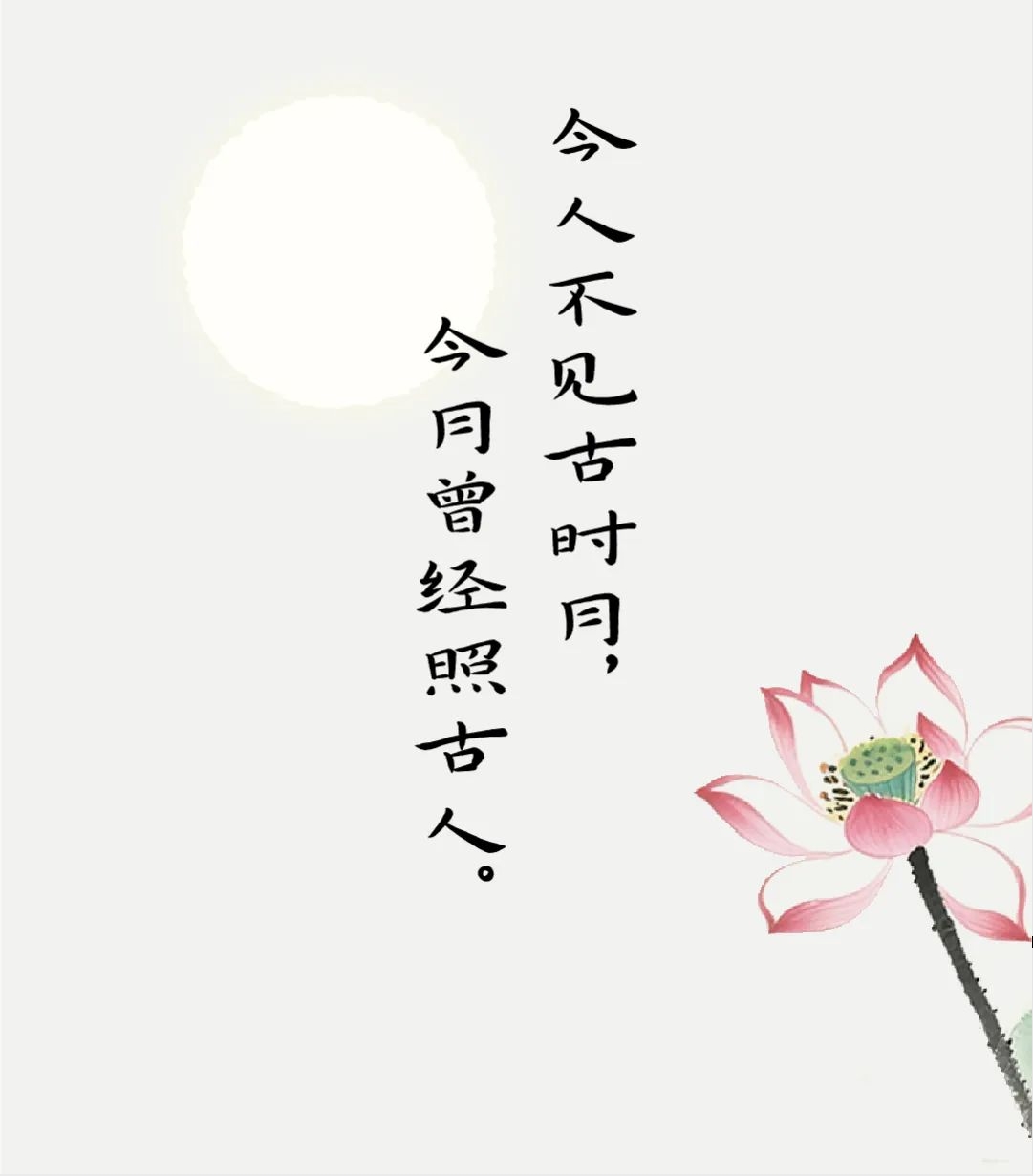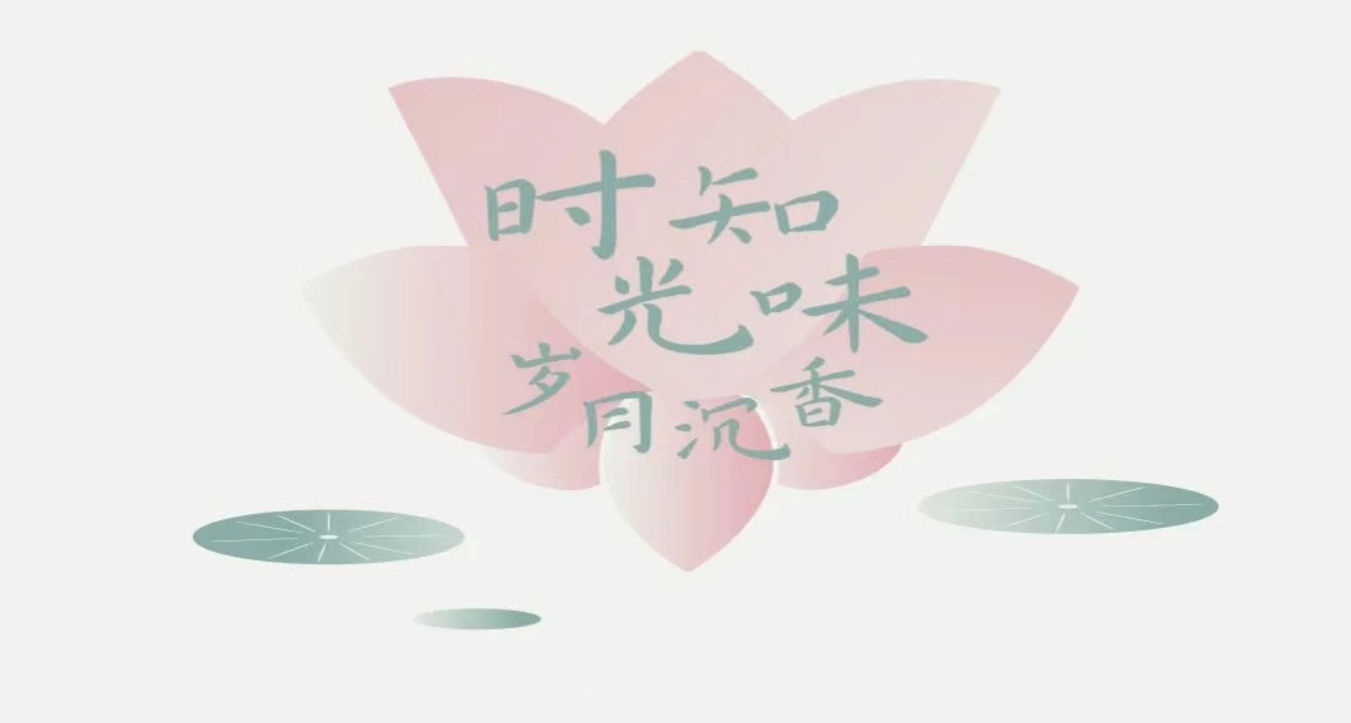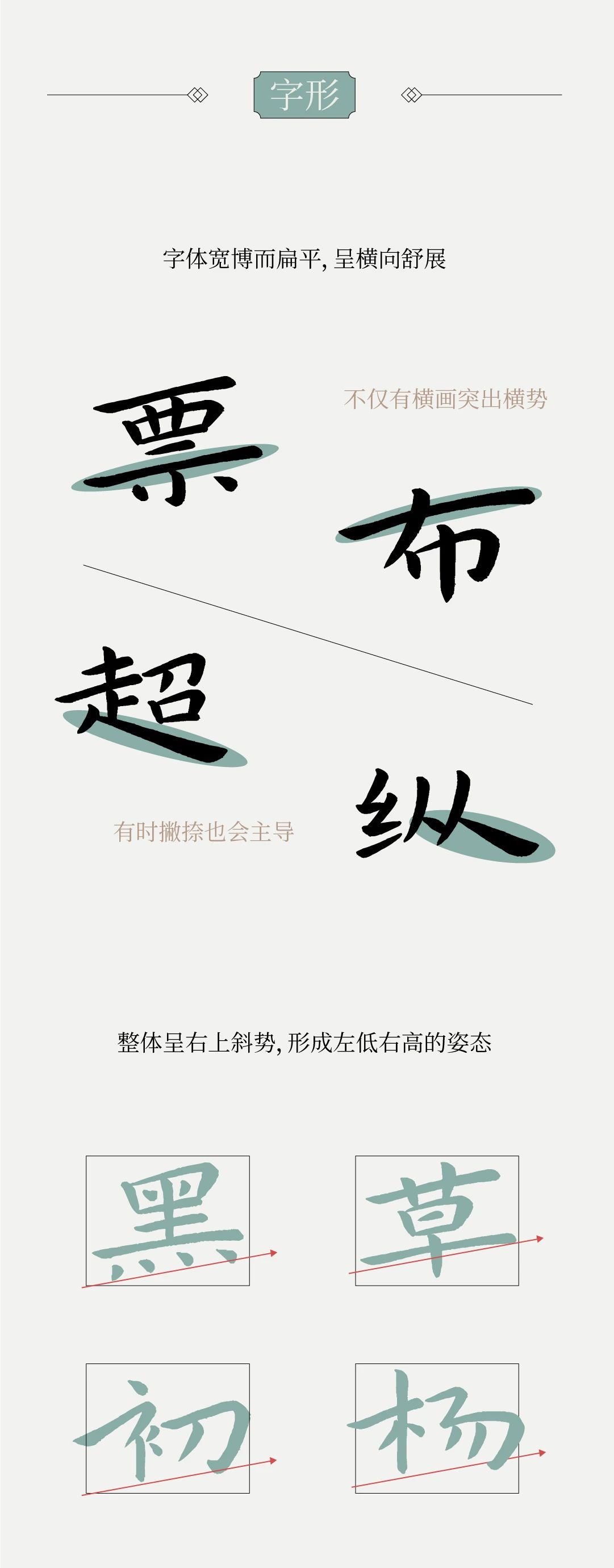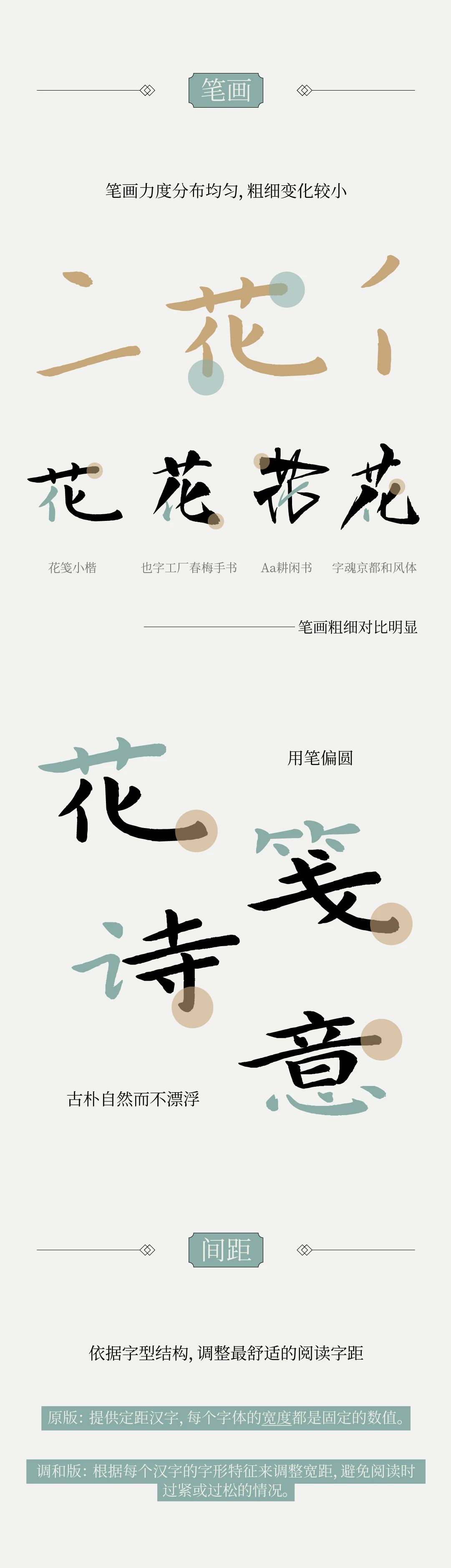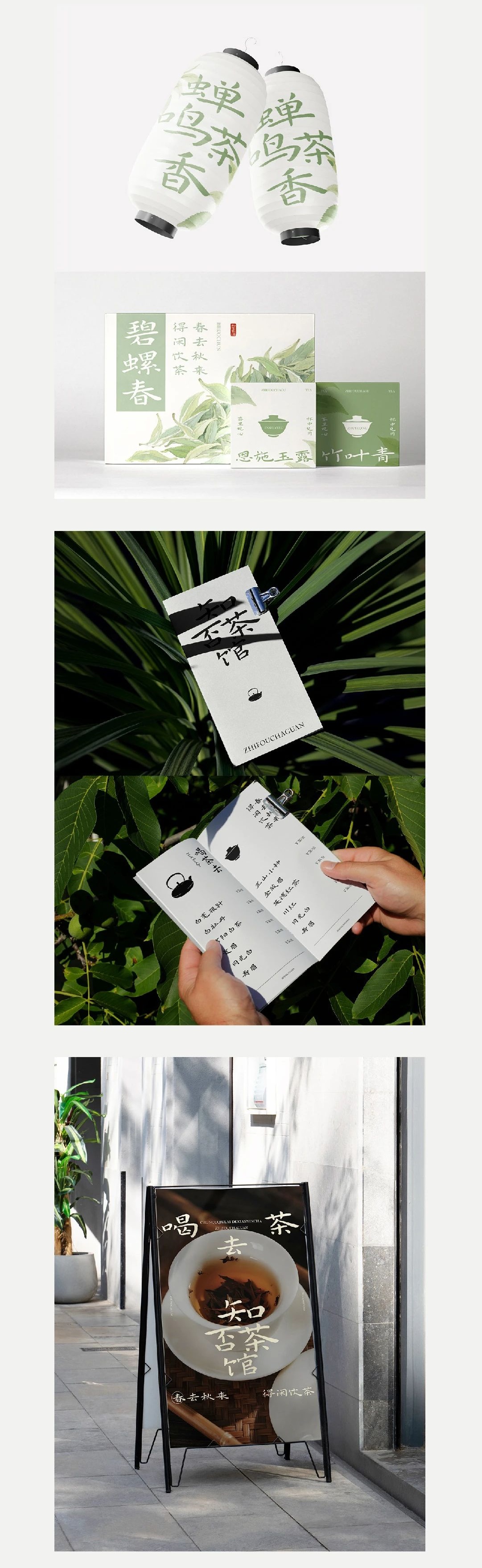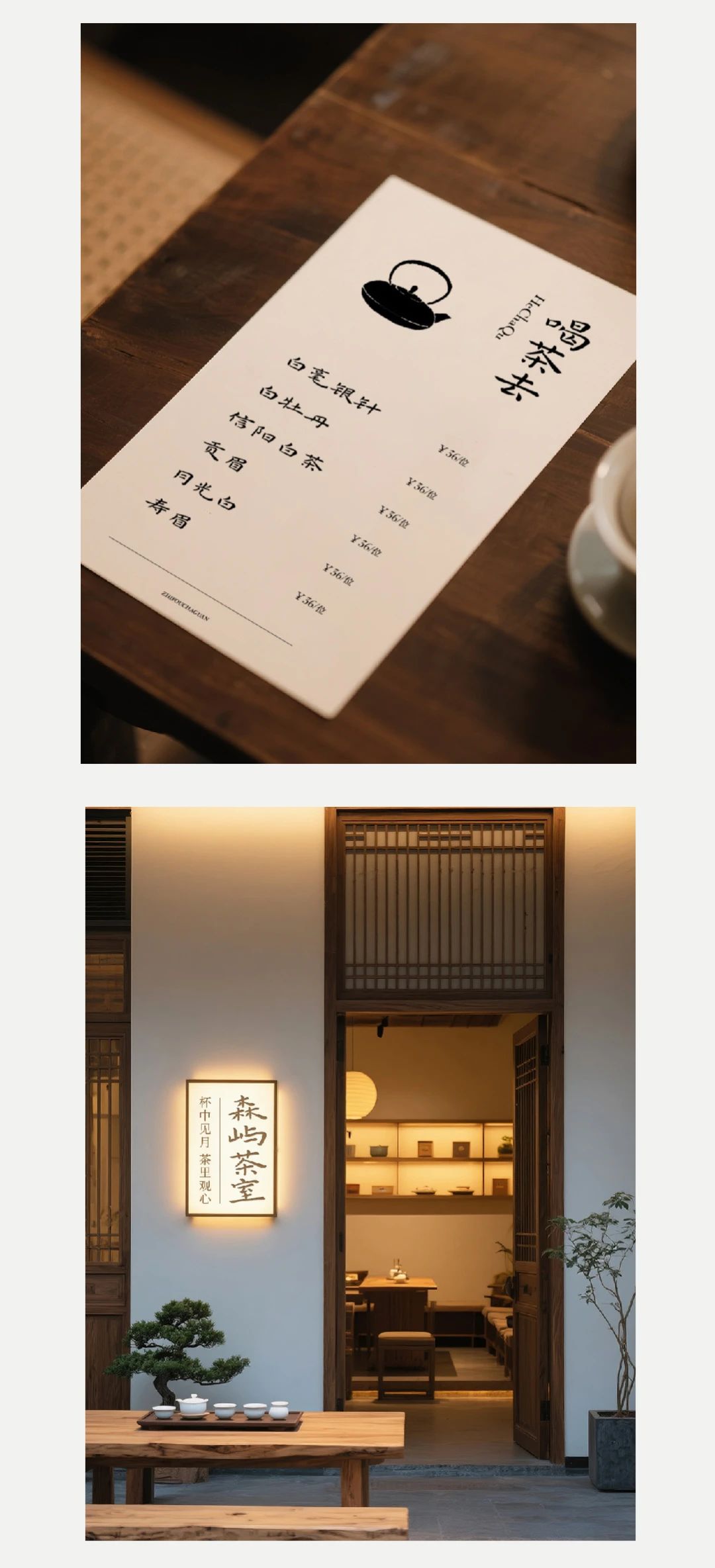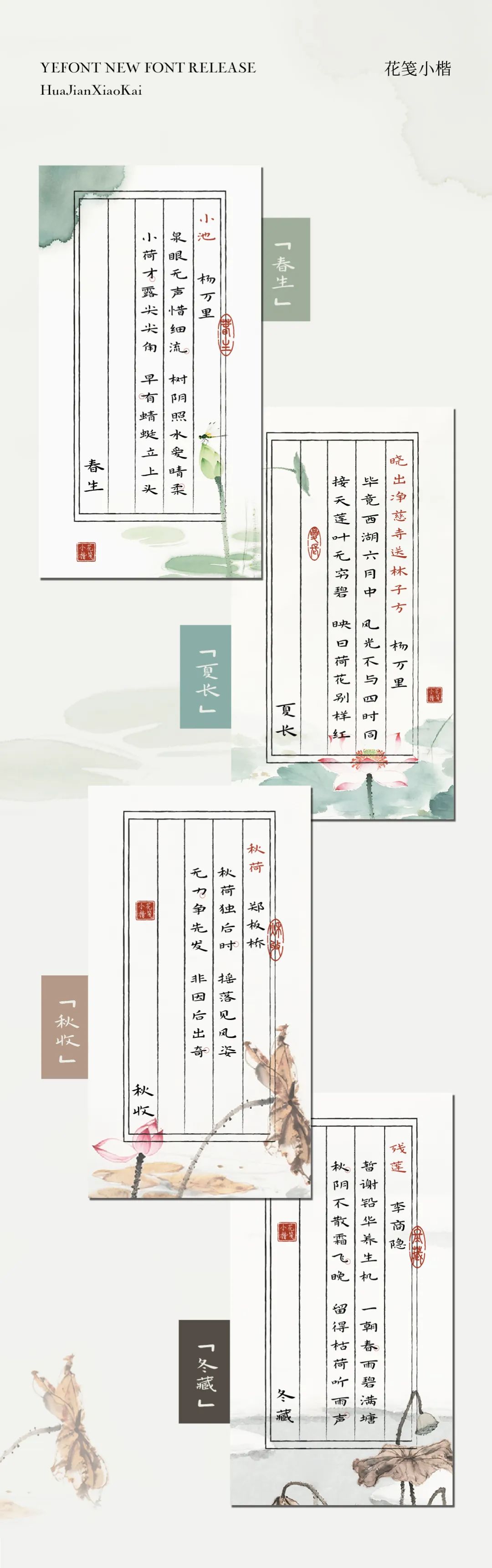
字体名称:也字工厂花笺小楷
花笺,一种印有花纹图式的古代笺纸,始于南朝。
古代的文人墨客流行用这种雅致的花笺纸,诗歌唱和、书信往来。更有甚者会自制笺纸,以山水花鸟等纹样为饰,赋予其“彩笺”“花笺”“锦笺”等美名。
然而世事更迭,花笺这一古物,在现代中已少见踪影。
但这种充满仪式感和艺术性的书写行为,其背后承载的古人雅致与风情,令现代人也十分向往。
惊叹于古人竟可以将方寸之物玩出“花”来同时,我们也从中得到了些许灵感
想要创作一套以花笺为主题的字体-【也字工厂花笺小楷】
这套字体取法自王宠《南华真经》和钟繇《宣示表》,二者都属于带有朴拙气质的小楷作品。相比于其它大开大合或风骨独特的书法字体,花笺小楷更像一款介于中间的字体。
有魏晋时代舒朗的间架结构,亦糅合了明清时代书卷气的点画特征,轻巧又不轻佻,朴素又不泯然于众,给人以朗月清风的观感。
小楷字形较小,天然拥有更大的字间距,作为正文字体使用也不会有太大的阅读压力。
所以,兼具古朴典雅和清丽飘逸气质的「花笺小楷」,适用于书刊、画册、报纸和杂志的内文排版,以及文化艺术、商业广告的宣传设计。